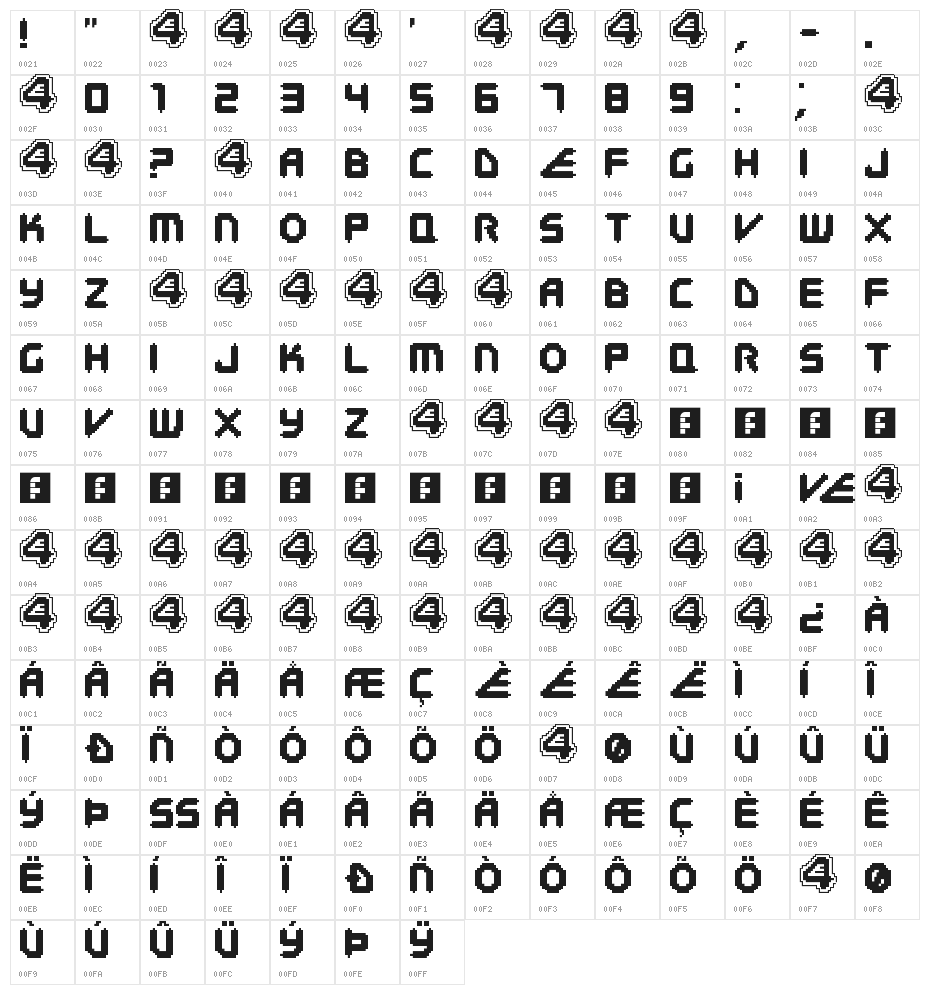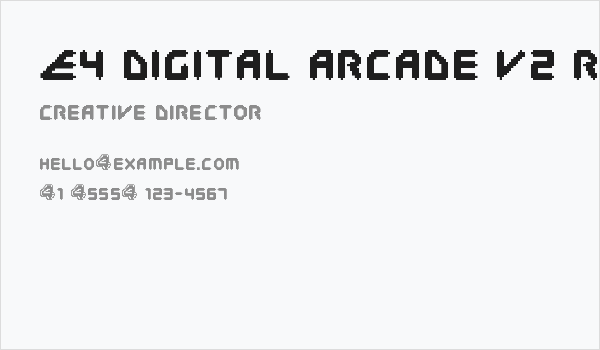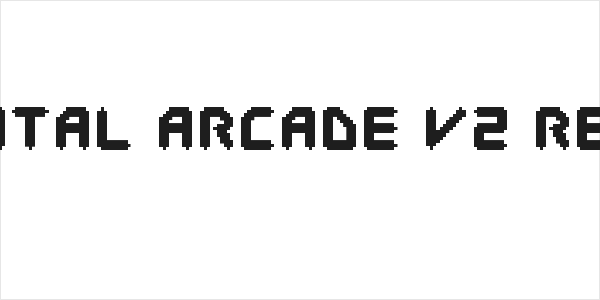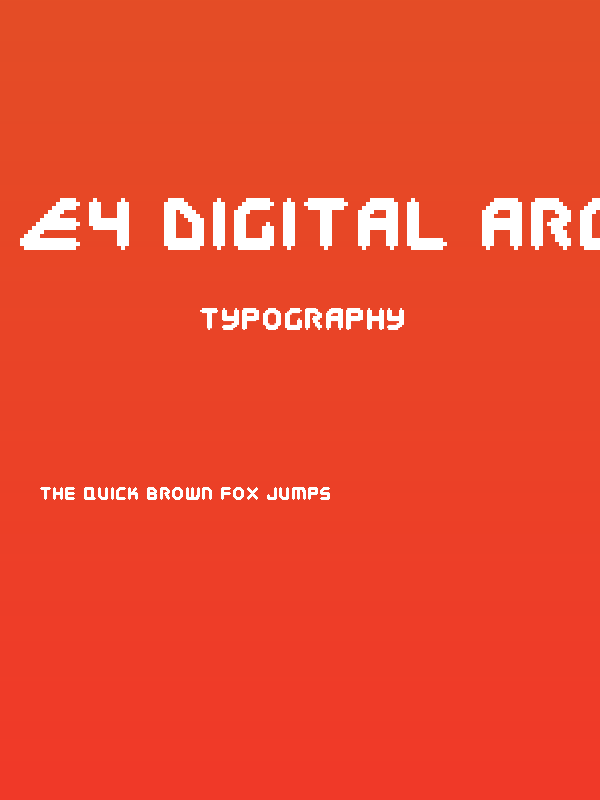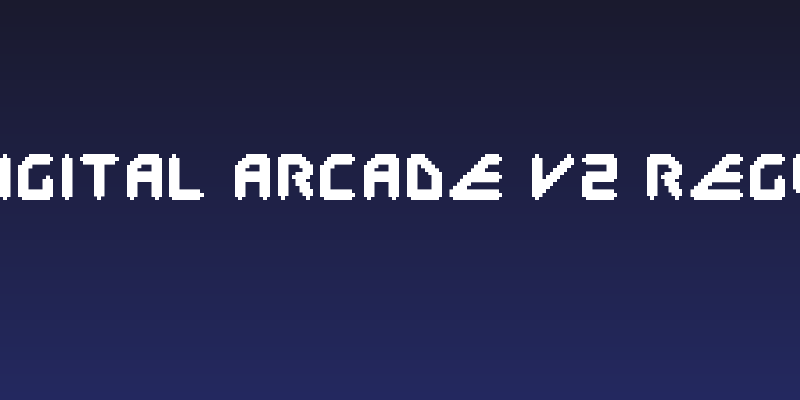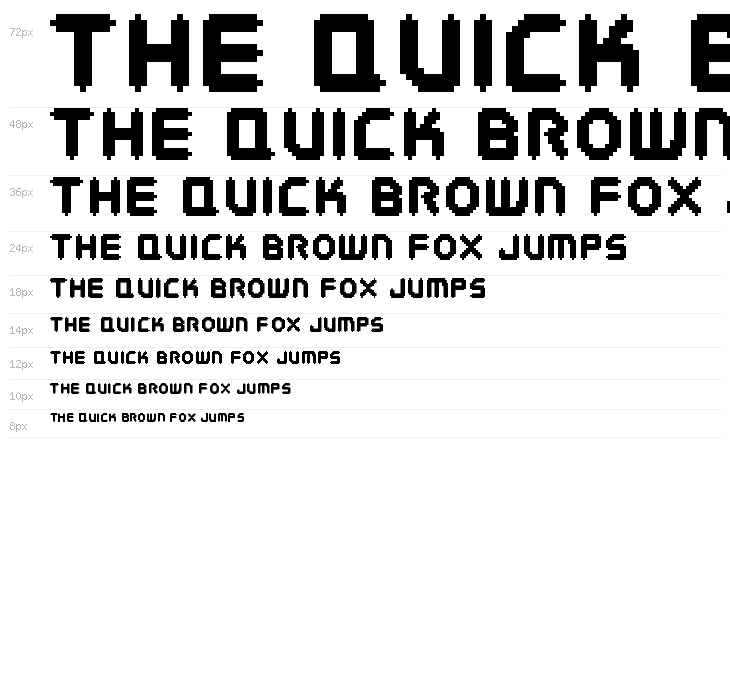
E4 Digital Arcade V2 Regular Font
| Gesamtstil | Retro, Digital |
| Vorgeschlagene Projekte | Ideal for video game design, retro-themed posters, digital art projects, and any creative work that seeks to capture the essence of classic arcade aesthetics. |